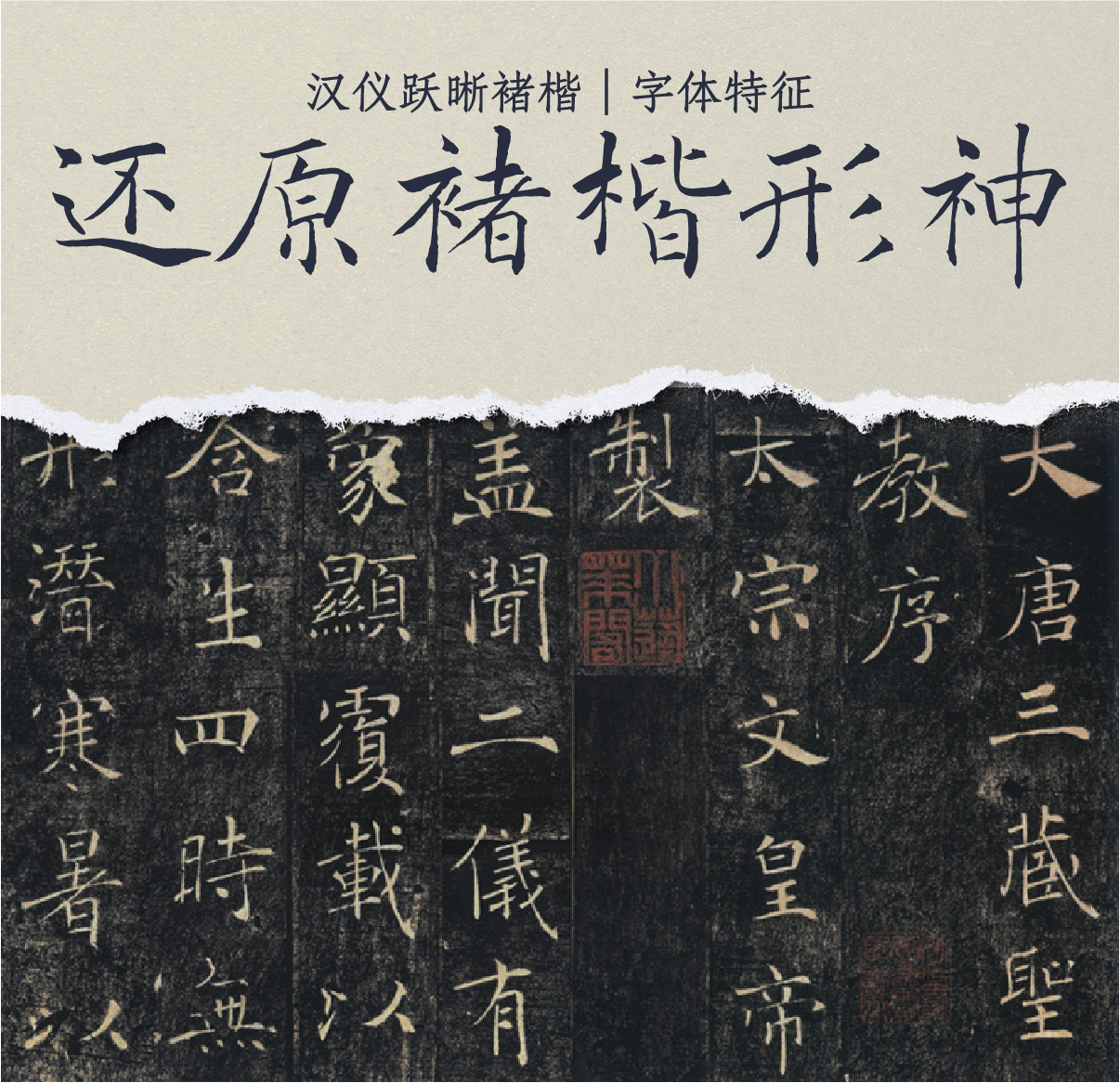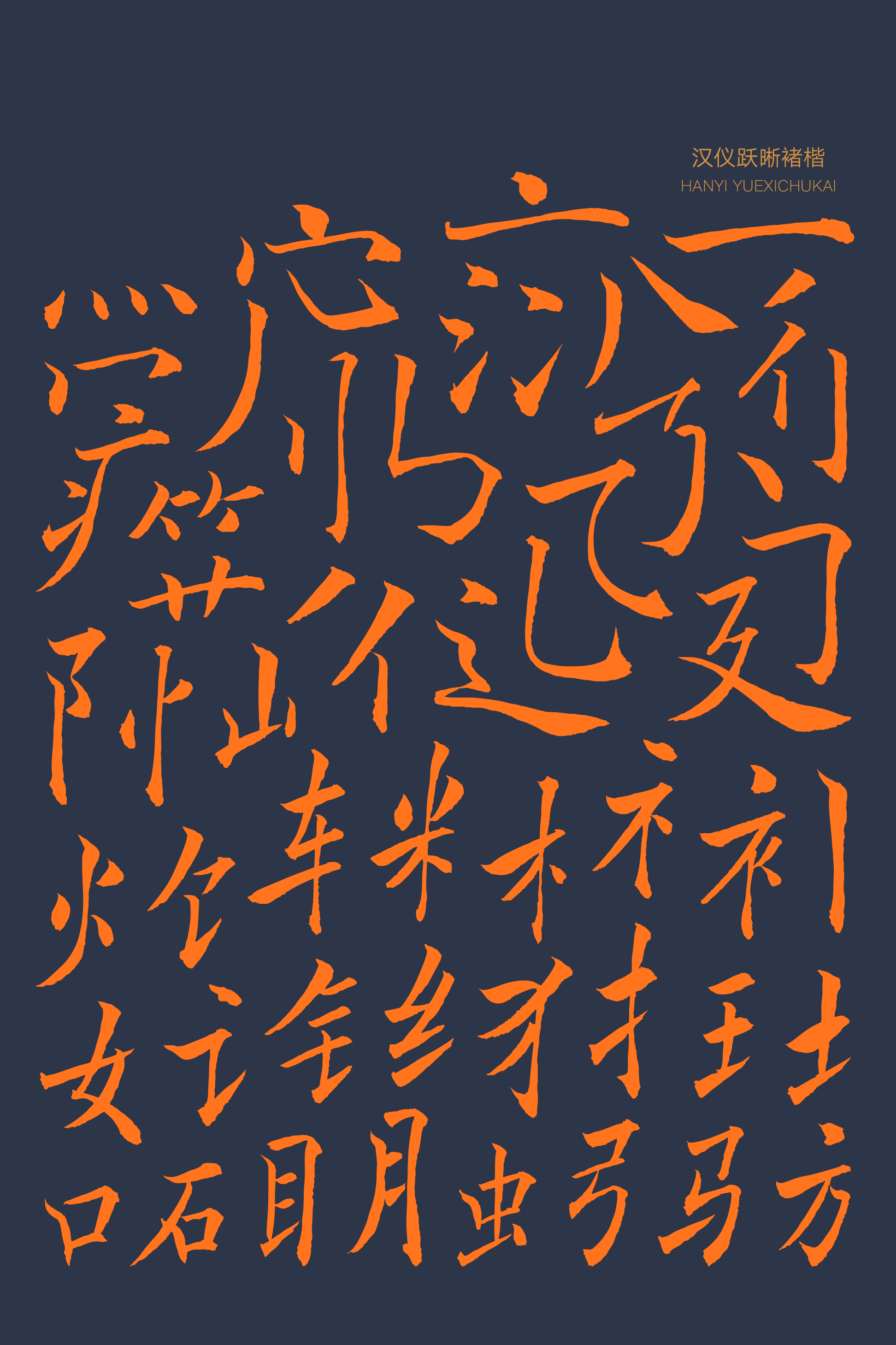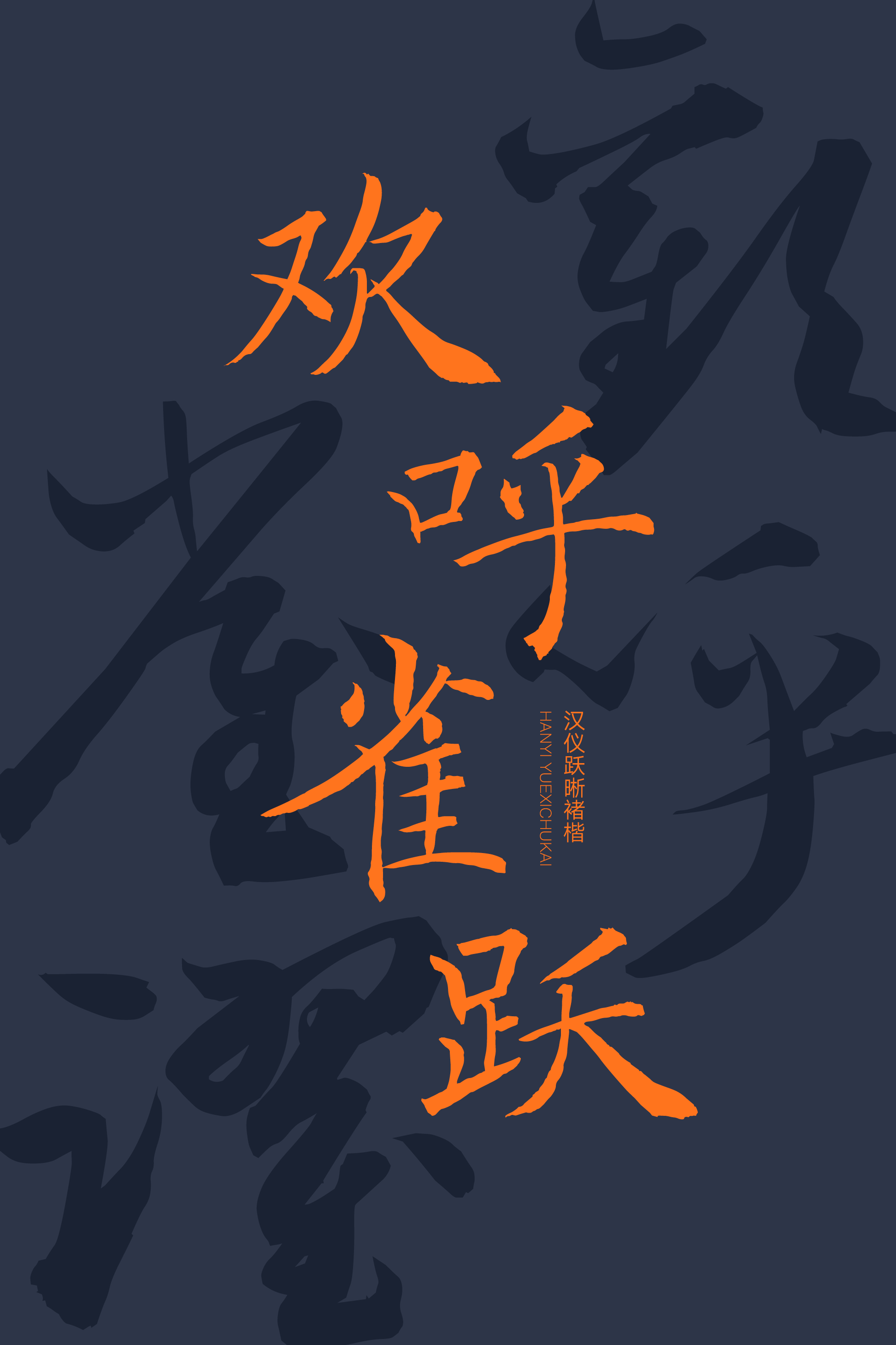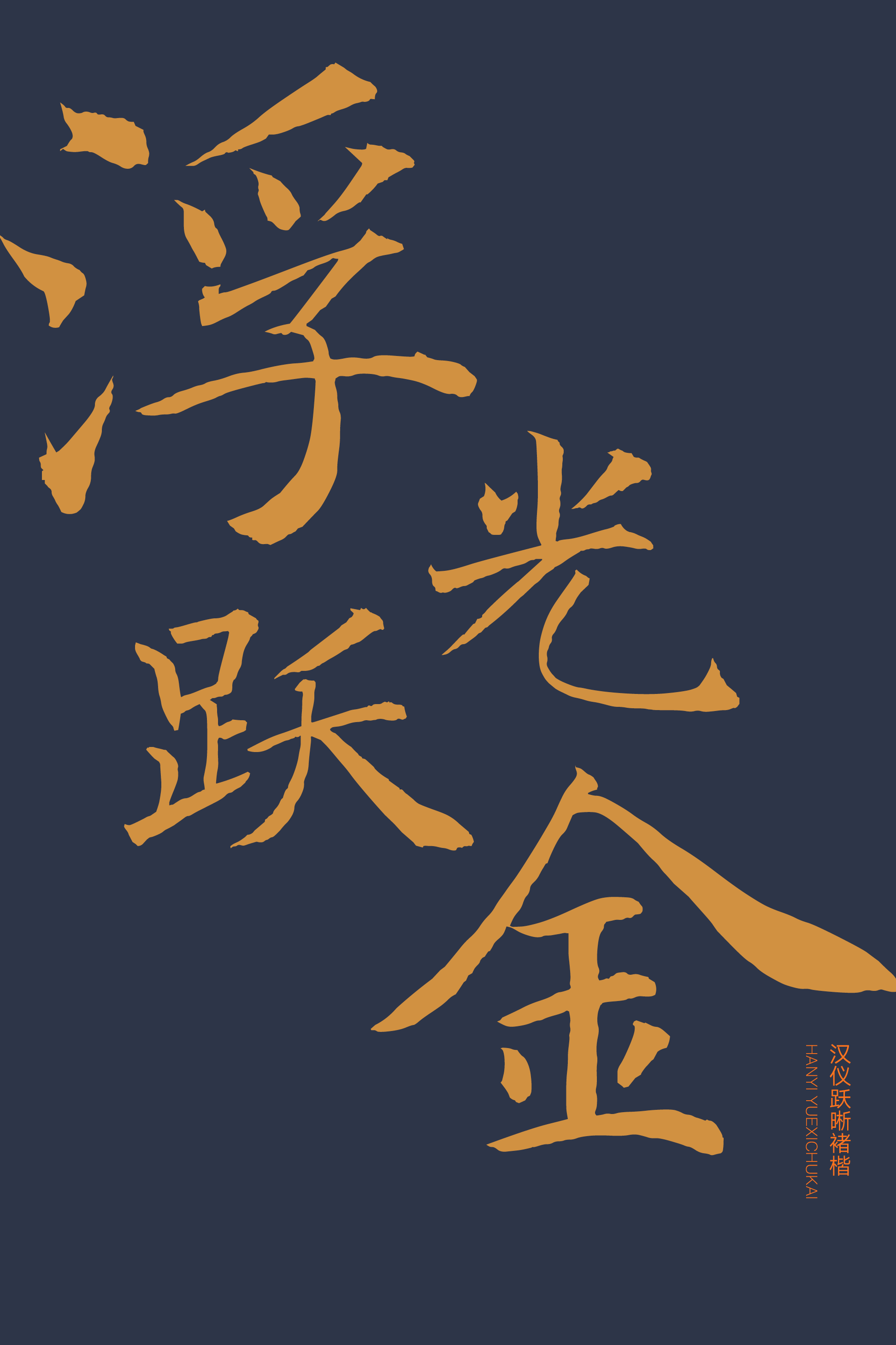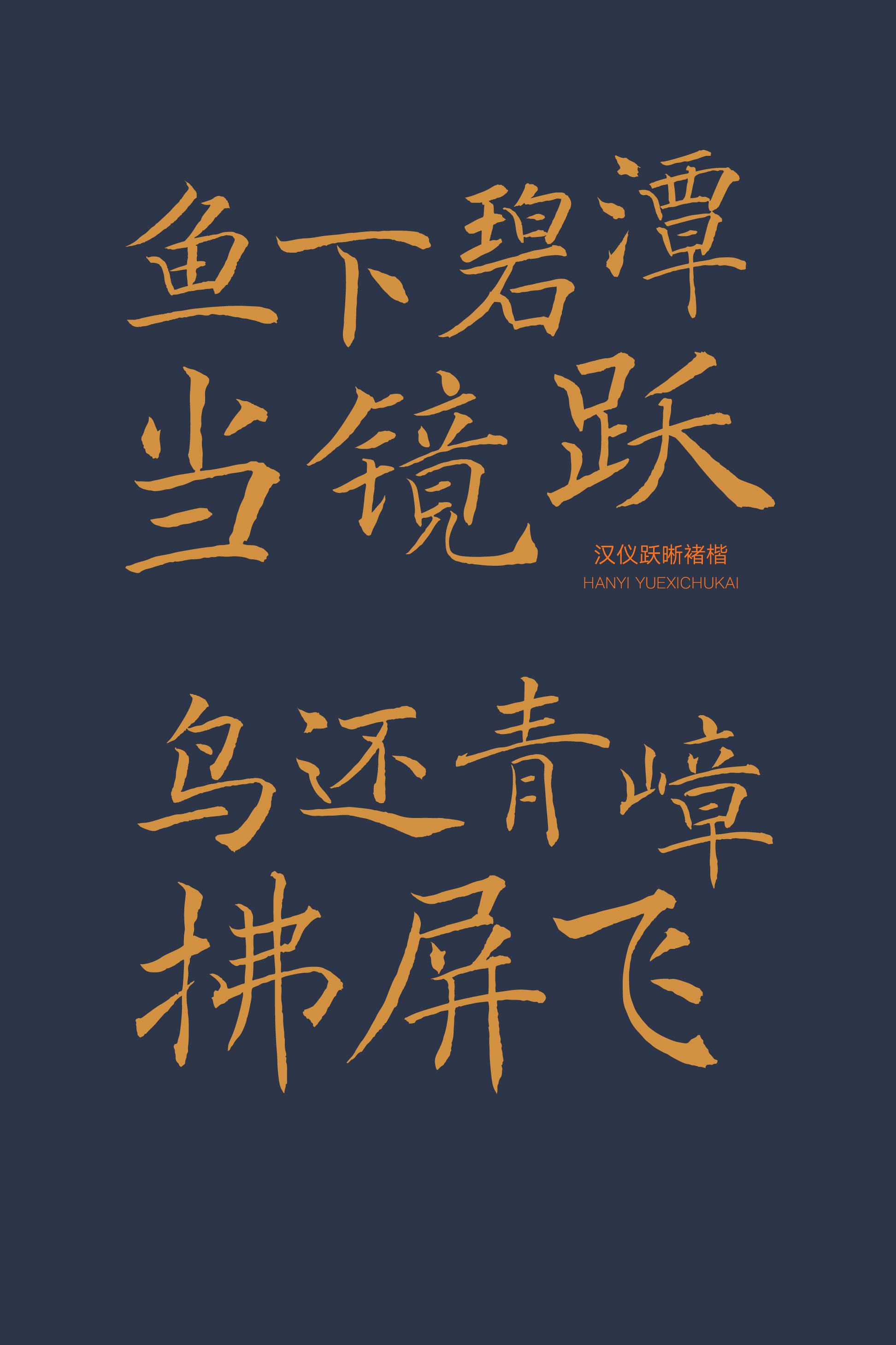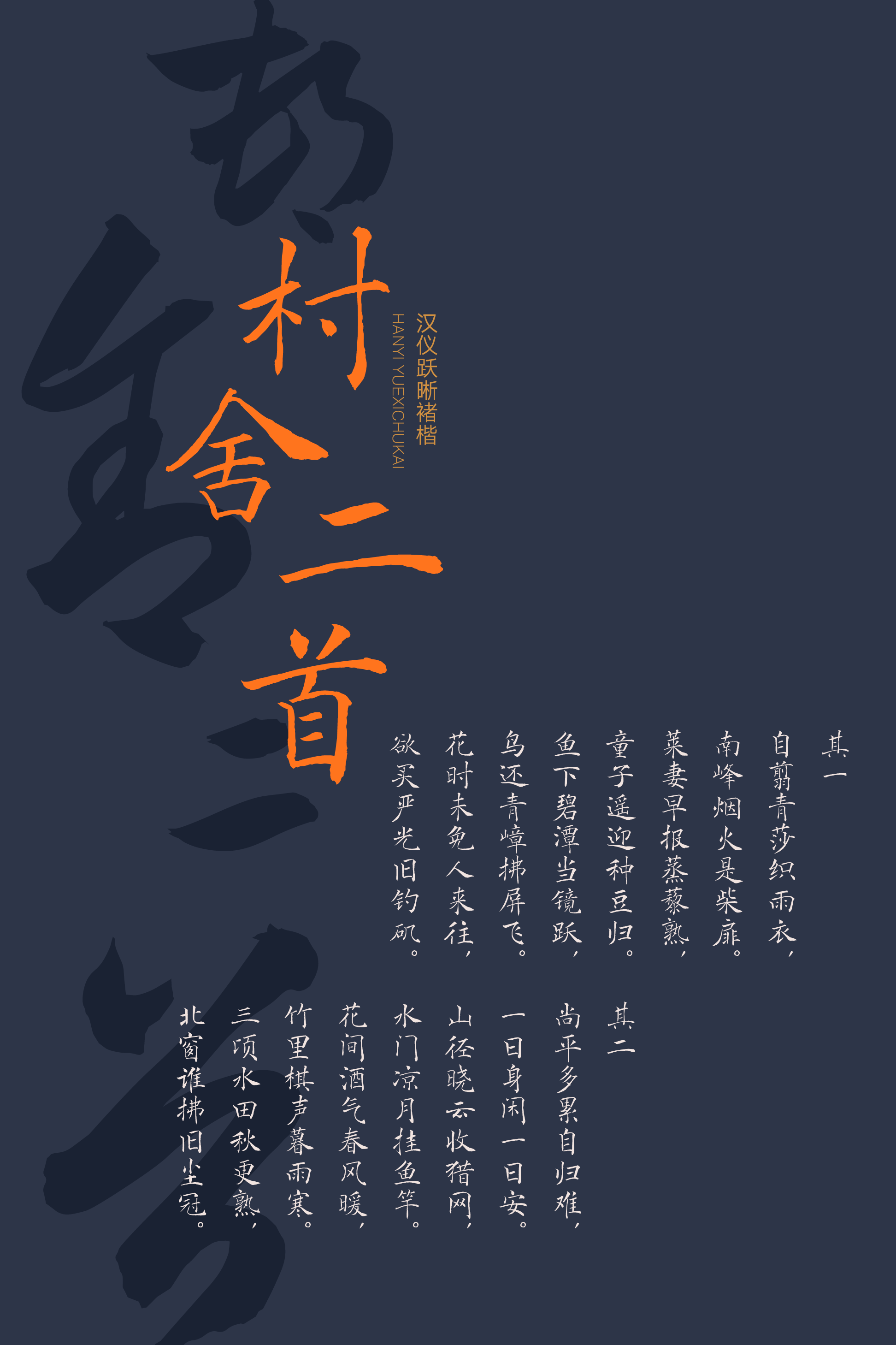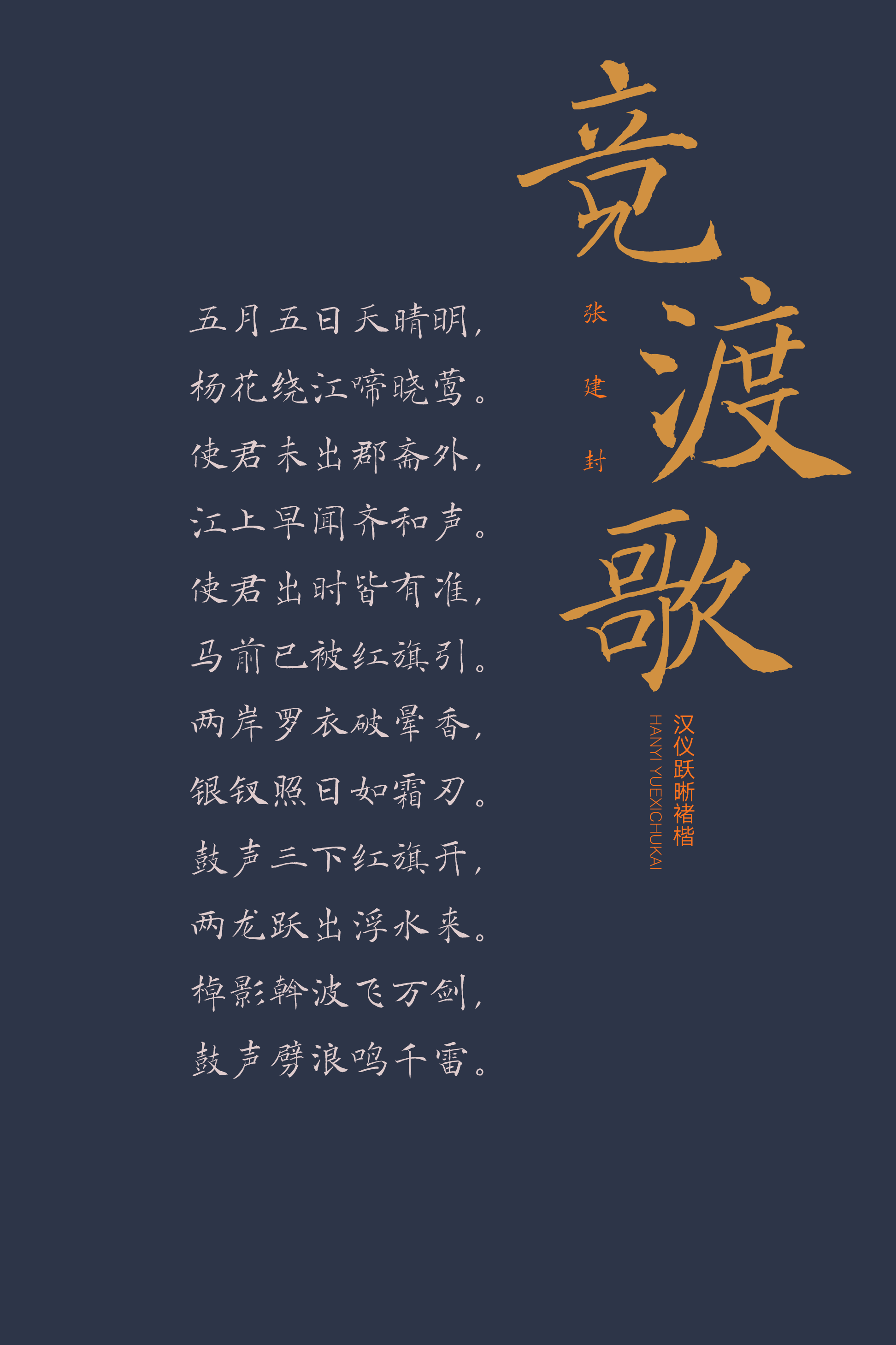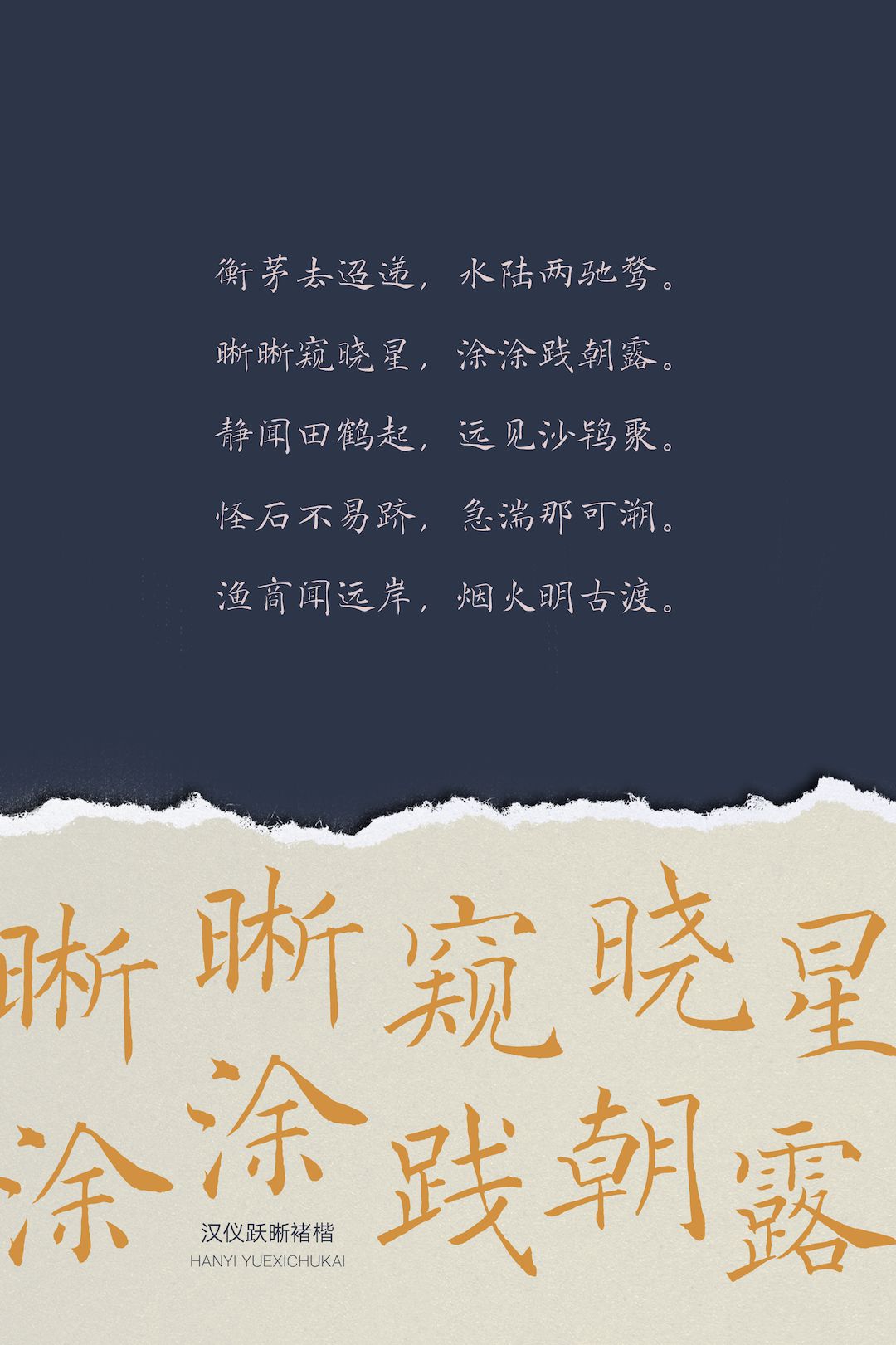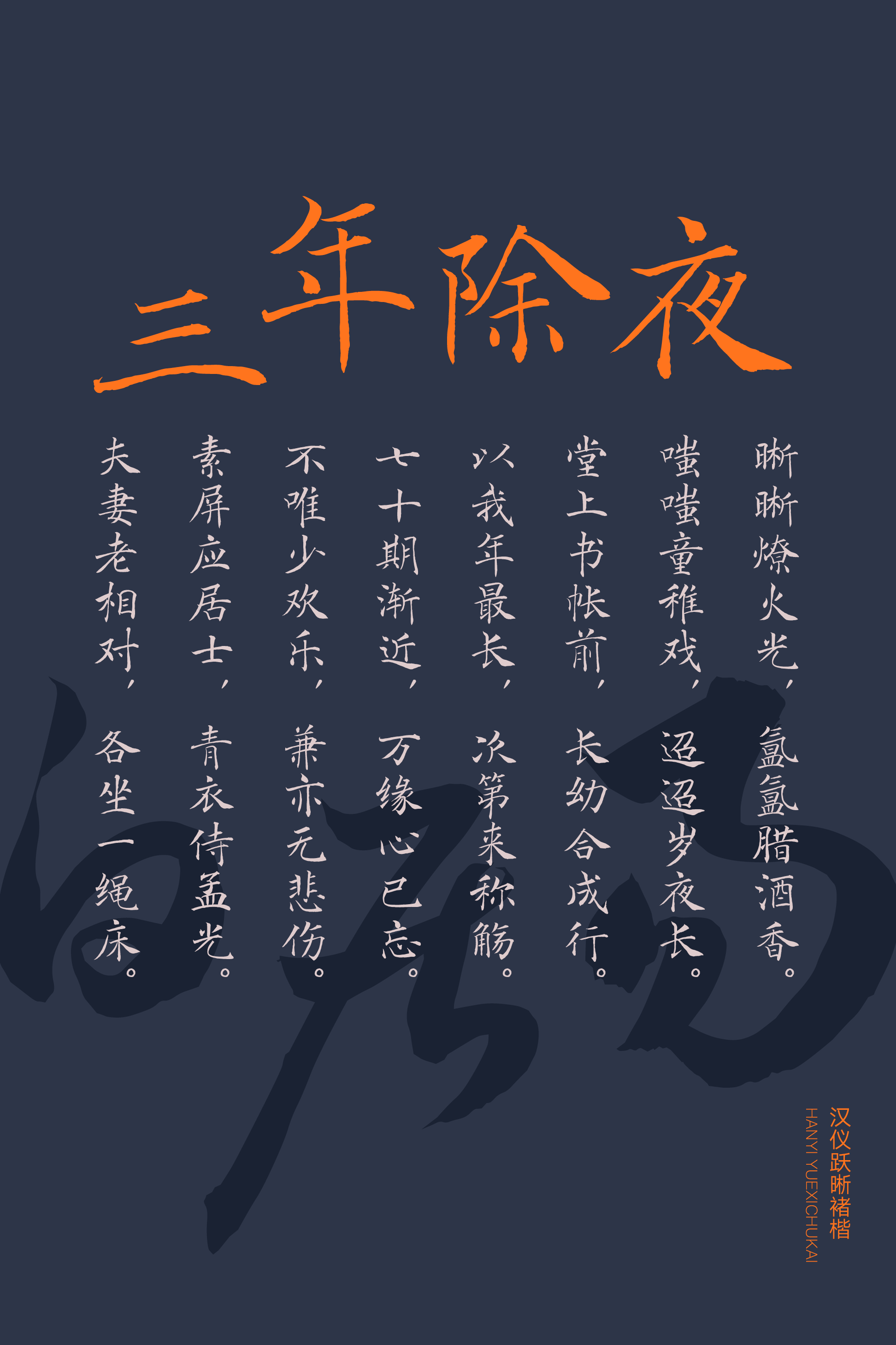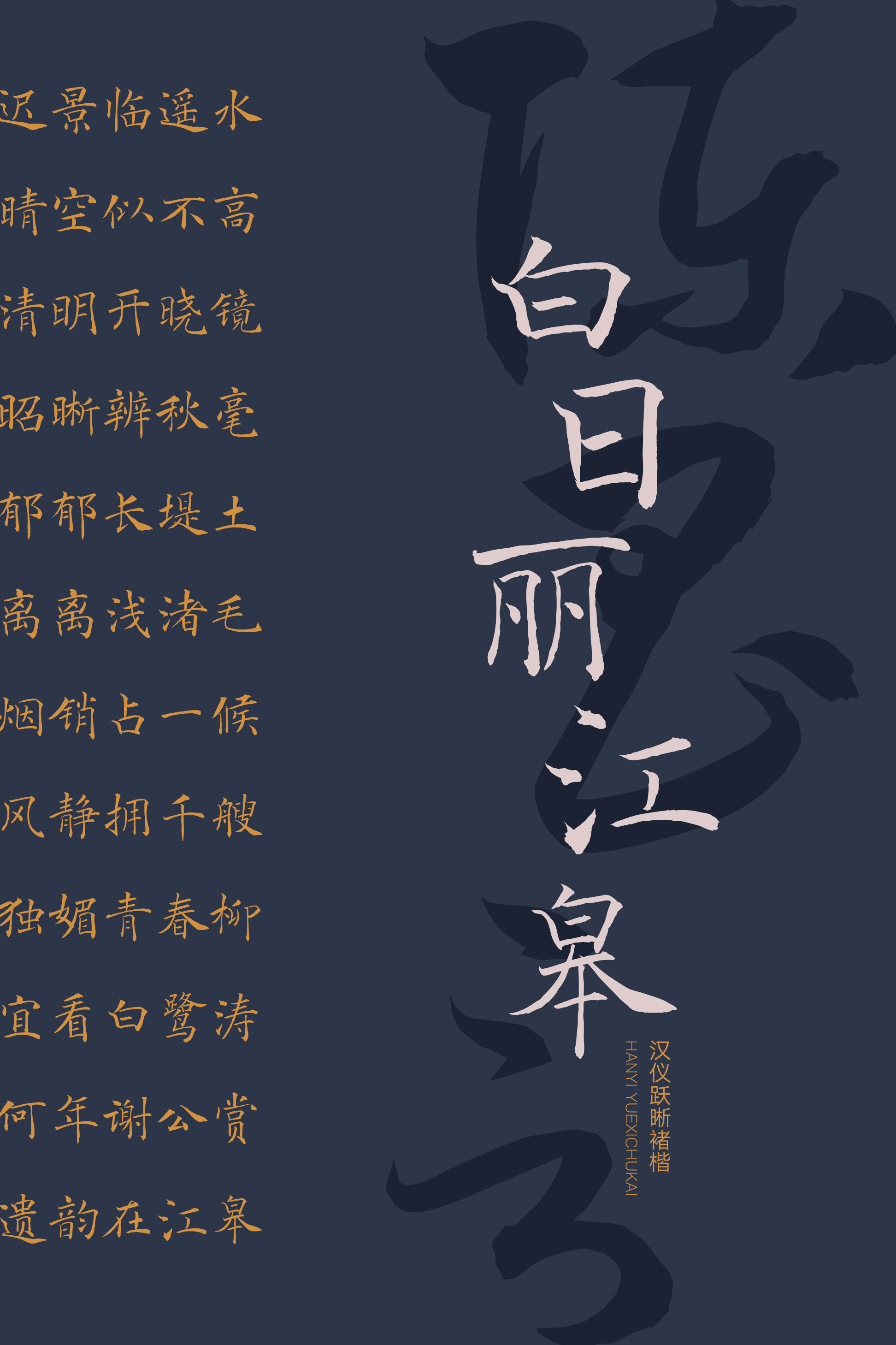
汉仪跃晰褚楷
汉仪跃晰褚楷,来源于初唐四大书家之一褚遂良的楷书作品《雁塔圣教序》,作者邵跃晰将自己临习、创作褚楷多年的经历和理解以书写字库的形式呈现,保留褚楷风貌,学其形神而非简单的描摹复制,使其适应于现代的使用环境。这款秀丽雅致的楷书书写字体既是对于褚体楷书的致敬、学习,也是将传统融汇于现代的再创造。
《雁塔圣教序》立于唐永徽四年,褚遂良书。褚遂良(596-658),工于书法,初学虞世南,后取法王羲之,与欧阳询,虞世南,薛稷并称“初唐四大家”。其特点是善把虞、欧笔法融为一体,方圆兼备,舒展自如。
褚遂良《雁塔圣教序》多隶意,呈分势扁形,考虑到现代字库多应用于横向排版, 过于扁势影响字间距的紧凑关系,为保留行气,在书写时略微拉高字形。
笔画生动,纤韧秀丽,相较于原帖的方圆结合、宛转流利,更偏重于方折,使其气韵挺拔。
西文部分同样以连贯的笔意书写而成。